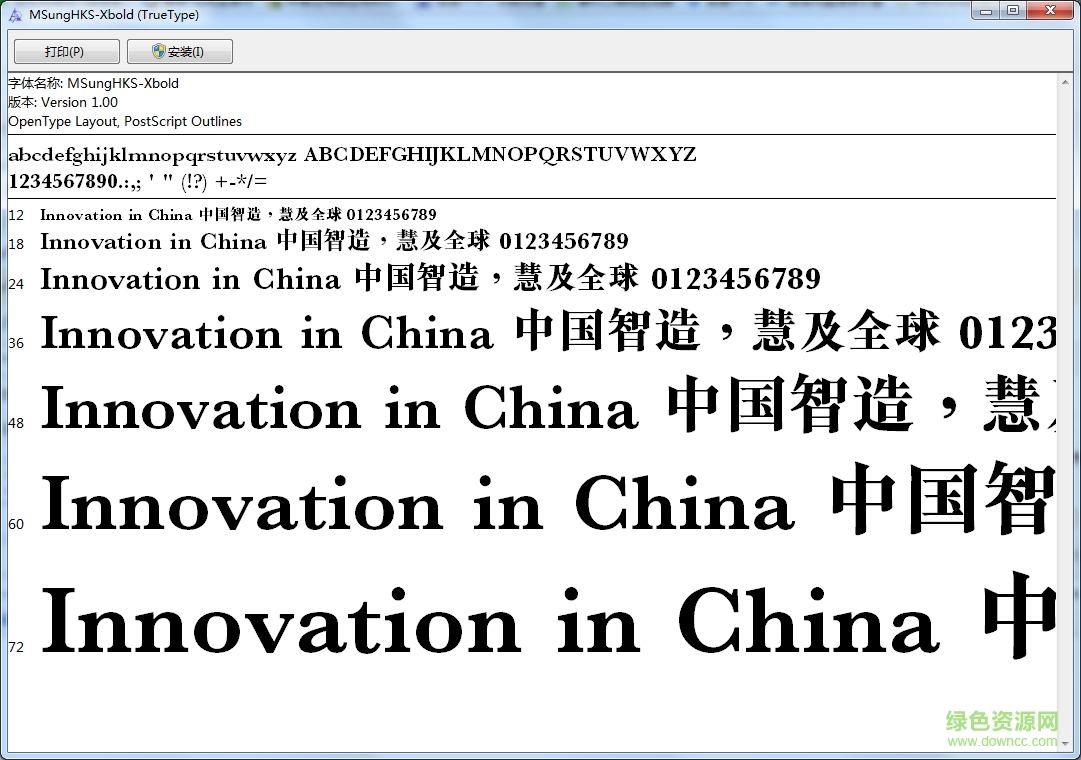
msunggb字體是一款橫細(xì)豎粗的襯線字體,字形和宋體差不多,方正勻稱,典雅好看,便于印刷和閱讀,實(shí)用性強(qiáng),各種中文的書(shū)刊雜志都是使用這類字體排版,歡迎大家免費(fèi)下載!
宋代刻版印書(shū)通行的字體。宋體結(jié)構(gòu)方正勻稱,橫細(xì)直粗,便于刻版,閱讀醒目,是16世紀(jì)以來(lái)漢字的主要印刷體。